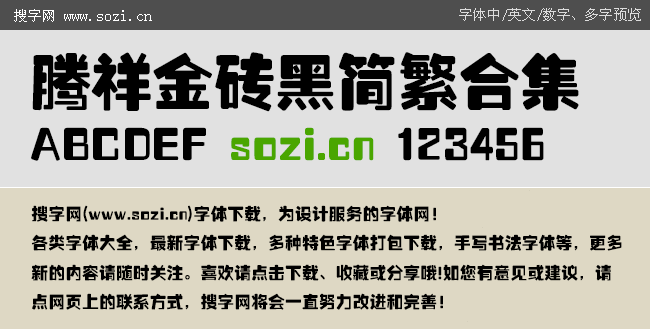
騰祥金磚黑簡(jiǎn)繁合集
搜字網(wǎng)提供一款騰祥金磚黑簡(jiǎn)繁合集中文藝術(shù)字體下載,騰祥金磚黑是一款應(yīng)用于設(shè)計(jì)方面的中文簡(jiǎn)體漢字,該字體風(fēng)格鮮明、特點(diǎn)突出,筆畫間搭配粗細(xì)懸殊,字的造型重上輕下,厚左薄右,形成字面上的黑白反差,比較“耀眼”,可適用于廣告設(shè)計(jì)、平面設(shè)計(jì)、印刷包裝、書法繪畫等領(lǐng)域。